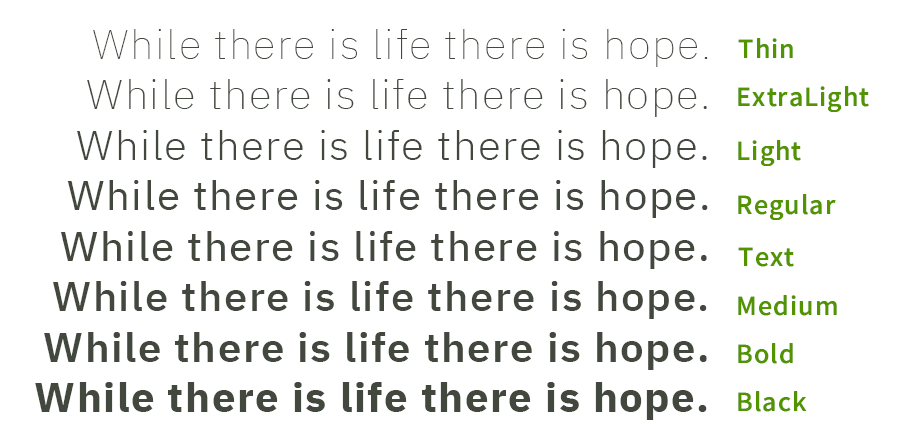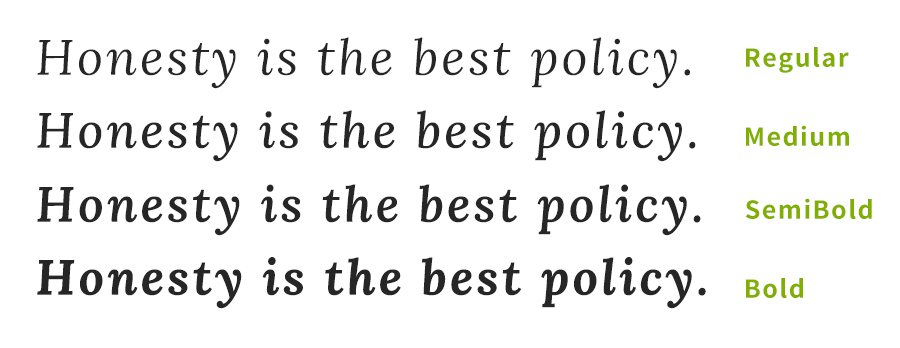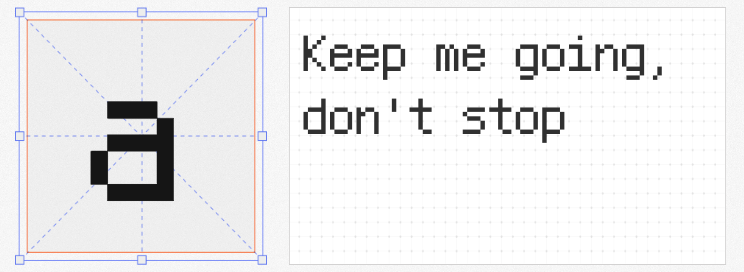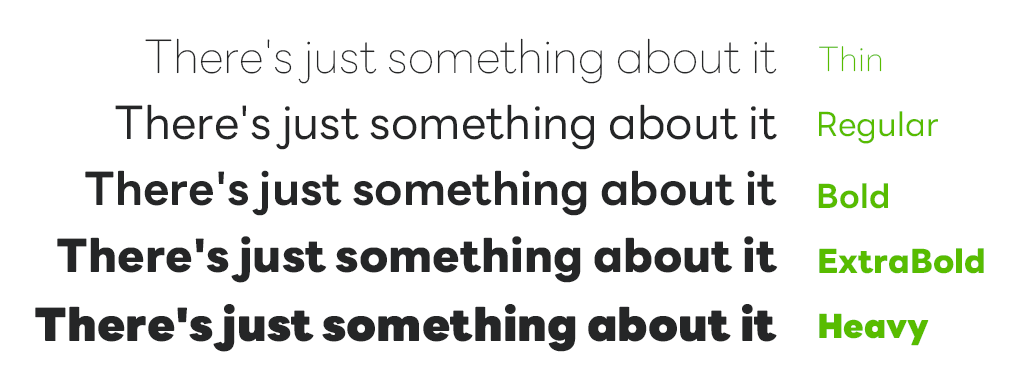
在全球化设计语境中,选择兼具视觉表现力与法律安全性的免费商用西文字体至关重要。以下四款风格迥异的开源字体,覆盖衬线、无衬线、像素与现代几何风格,满足从品牌主视觉到创意排版的多元需求。
1. Lora Italic
这款受传统书法启发的衬线字体,以优雅的倾斜角度与动态笔画传递人文气息。设计师通过控制字重对比与衬线弧度,让Lora Italic既能驾驭文艺杂志的标题设计,也能为品牌故事长图注入流动感。其独特的“印刷声音”特别适合需要营造沉浸式阅读体验的场景,如咖啡馆菜单、独立书店视觉系统或文化类短视频字幕。
在8-bit美学复兴的当下,这款专为低分辨率设计的像素字体成为数字怀旧风的利器。通过精确控制每个像素点的排列,12px版本在保持黑体简洁性的同时,完美还原了复古游戏机的视觉质感。适用于科技品牌周年海报、独立游戏UI或音乐专辑封面等需要制造年代错位感的场景,用极简元素唤醒Z世代的集体记忆。
由LINE联合五国设计团队打造的这款超细体,将日本传统书写韵味与现代无衬线结构巧妙融合。较大的中宫设计确保了小字号下的可读性,而圆润的笔画末端则传递出友好亲和的企业形象。特别适合亚洲市场的互联网产品界面、社交媒体图文排版或文创产品包装,在保持专业感的同时注入“微笑大人”的温暖气质。
作为Helvetica的替代方案,这款由IBM主导开发的字体系统展现了理性与人文的平衡。简洁的几何结构暗含网格系统的秩序感,而适度的人性化细节调整(如略微收窄的e字母)则避免了过度机械化的冰冷。其开源特性使其成为科技公司品牌升级的热门选择,从数据可视化图表到开源社区文档,都能通过统一字体语言强化专业信任感。